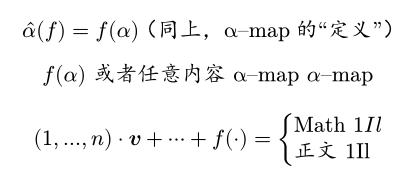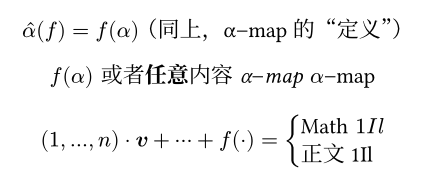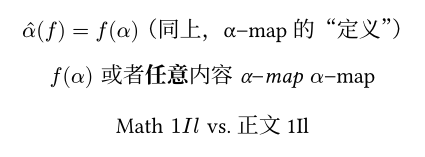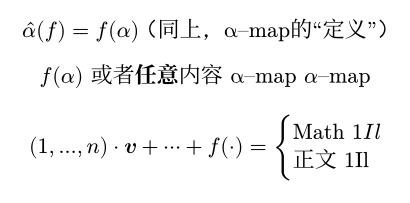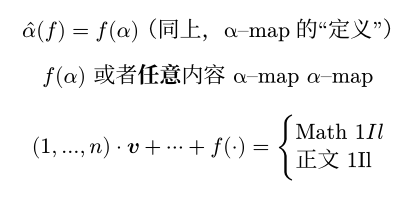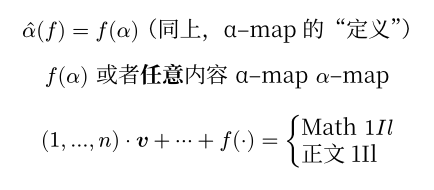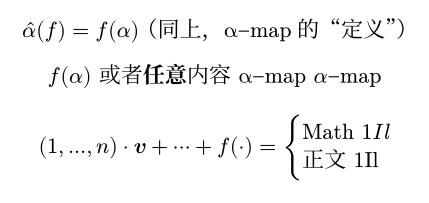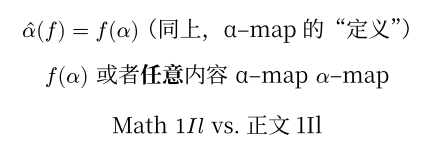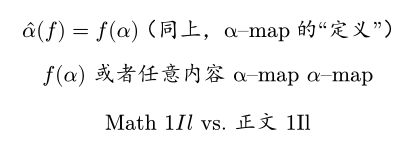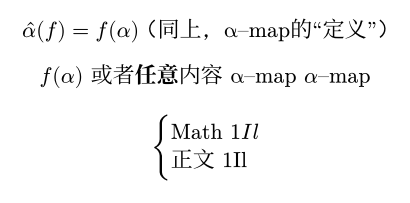
如何修改公式里的中文字体?
若不专门设置,公式中的中文通常是楷体:
typst
$ hat(alpha)(f) = f(alpha) "(同上,α–map的“定义”)"$
$ f(alpha) #[或者*任意*内容 _α–map_ $alpha$–map] $
$ (1,...,n) dot bold(v) + dots.c + f(dot.c) = cases("Math" 1 I l, "正文 1Il") $
配置正文字体后,请按以下任一方法继续设置数学公式的字体。
“引号”泛指中西共用标点
下文所谓“引号”并不专指单双引号,而泛指中西共用标点,具体包括:
• Latin-1 Supplement:
• U+00B7 · MIDDLE DOT, $dot.c$ (≠ $dot$ = $dot.op$)
• General Punctuation:
• U+2013 EN DASH
• U+2014 EM DASH
• U+2018 LEFT SINGLE QUOTATION MARK
• U+2019 RIGHT SINGLE QUOTATION MARK
• U+201C LEFT DOUBLE QUOTATION MARK
• U+201D RIGHT DOUBLE QUOTATION MARK
• U+2025 TWO DOT LEADER
• U+2026 HORIZONTAL ELLIPSIS, $...$ (= $dots.h$$dots.c$ = $dots.h.c$)
• U+2027 HYPHENATION POINT
• Supplemental Punctuation:
• U+2E3A TWO-EM DASH
参考Typst 源代码中的 Covers::LatinInCjk
若引号想用数学字体(数学、西文字体统一)
此法最简洁,且对数学部分干扰最小,推荐使用。
#show math.equation: set text(font: (
"New Computer Modern Math", // 数学
"Source Han Serif SC", // 中文
))
若引号想用中文字体(数学、西文字体统一)
有两种思路。第一种在数学字体前单独选择要使用的标点。这里没有选择间隔号·与省略号……,因为它们也可能用作数学符号。
#show math.equation: set text(font: (
(name: "Source Han Serif SC", covers: regex("[–—‘’“”‥‧⸺]")), // 中文
"New Computer Modern Math", // 数学
"Source Han Serif SC", // 中文
))
第二种从数学字体排除所有中西共用标点。
#show math.equation: set text(font: (
(name: "New Computer Modern Math", covers: "latin-in-cjk"), // 数学
(name: "Source Han Serif SC", covers: regex(".")), // 中文
"New Computer Modern Math", // 数学
))
Typst 0.14 会将首个没有covers的字体用作数学基准字体,从中提取间距等数学排版信息。因此,中文字体若在数学字体之前,必须设置covers: regex("."),不然中文字体会被误当做数学基准字体,导致数学间距异常,并让你满篇文章都有警告。
其它方法(数学、西文字体分开)
如果您真的需要,也可以分开设置数学和西文字体。不过请注意以下问题。
1. 数学公式中,文本($"x"$$#[x]$)和正体变量($upright(x)$)使用相同字符,无法分开设置字体。以下几种方法中,它们都会变成西文字体。
类似地,数字$1$$"1"$也无法区分。以下几种方法中,它们仍使用数学字体。
2. 数学公式中有些普通字符需要数学特性。例如cases的大括号,就字符而言只是普通的{,而排版时需随内容拉伸。西文字体虽然也提供这些字符,但不支持数学,无法使用。
因此,西文字体的covers不能使用latin-in-cjkregex("."),必须换成范围更小的正则表达式。
具体设置方法如下。
如果引号想用中文字体
#show math.equation: set text(font: (
(name: "Libertinus Serif", covers: regex("[.\d\p{Latin}]")), // 西文
(name: "Source Han Serif SC", covers: regex("[·–—‘’“”‥…‧⸺]")), // 中文
"New Computer Modern Math", // 数学
"Source Han Serif SC", // 中文
))
如果引号想用西文字体
#show math.equation: set text(font: (
(name: "Libertinus Serif", covers: regex("[.\d\p{Latin}·–—‘’“”‥…‧⸺]")), // 西文
"New Computer Modern Math", // 数学
"Source Han Serif SC", // 中文
))
如果引号想用数学字体
#show math.equation: set text(font: (
(name: "Libertinus Serif", covers: regex("[.\d\p{Latin}]")), // 西文
"New Computer Modern Math", // 数学
"Source Han Serif SC", // 中文
))
#5305 目前可以对不同字符分别设置不同的字体。
配置正文字体后,请继续设置数学公式的字体:
#show math.equation: set text(font: (
(name: "Libertinus Serif", covers: "latin-in-cjk"), // 西文
"Source Han Serif SC", // 中文
"New Computer Modern Math", // 数学
))
上例使用 v0.13.1 编译,可能不适用于最新版。
1. 西文字体,负责 123abc,"!、{}()
Libertinus Serif 是 typst 内置的字体,可换为其它西文字体。
注意此处不建议设为 New Computer Modern,不然会导致大括号无法伸缩等问题。
2. 中文字体,负责汉字和,“”!
Source Han Serif SC 可换为其它中文字体。
3. 数学字体,负责公式中的复杂排版
New Computer Modern Math 是 typst 内置的字体,可换为其它支持 OpenType 数学特性的字体。
若计划中西共用同一字体
可合并前两项,例如:
#show math.equation: set text(font: (
"Source Han Serif SC",
"New Computer Modern Math",
))
上例使用 v0.13.1 编译,可能不适用于最新版。
注意这里第一处_α–map_没有倾斜,因为 Source Han Serif SC 缺少相应字形。
此外,不建议设置 #show math.equation: set text(fallback: false)
如果你使用旧版本,请使用以下旧方案。
使用 regex("\p{script=Han}") 匹配中文。
#show math.equation: it => {
show regex("\p{script=Han}"): set text(font: "Source Han Serif SC")
it
}